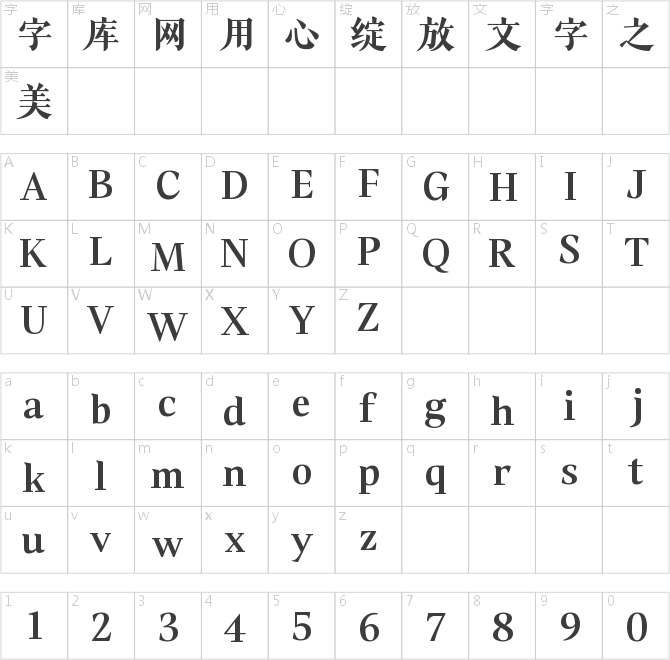
明体
山海汲古明刻,是一款国风复古刻本字体,包含简体汉字6763个,字形秉承中国明代古籍善本之字形特性,版刻刀法剔透,字形方正,端庄严谨,古朴大方,起落顿笔有棱角。在饱有笔墨之意的同时,又突显刀刻之锋美,笔刀结合刚柔并济。在秉承笔形间创新,结合当代设计视觉环境,融入现代审美,适用场景更多元,笔画造型清晰锐利,删繁取简,笔锋凌厉,速度感强,粗细对比强烈,重现刀刻古韵之美。